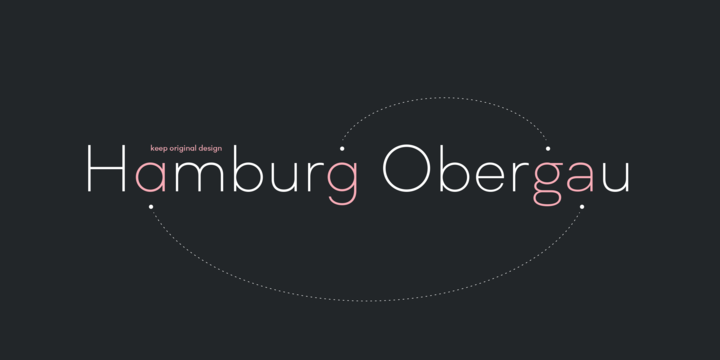
Ich glaube, die Xaloc hatten wir hier noch nicht. 24 Fonts für 120 Euro, sehr gut ausgebaut mit Caption-, Text- und Display-Schnitten, Small Caps und Versal-Eszett (auch als Small Caps regular und kursiv):
Bis morgen gibt es bei MyFonts die gut ausgebaute Kareemah sehr günstig (»ligatures, alternates, small caps,old style figures, fractions, superiors, inferiors and more« – das »more« beinhaltet unter anderem auch ein Versal-Eszett):
Leider ist ẞ anscheinend nicht als U+1E9E kodiert, sondern nur als Kapitälchen enthalten. Und die ungarischen Vokale passen mal wieder nicht. :cry:
Zu FUSE V.2:  Habe die Pakete mal gekauft u. festgestellt, daß beim TEXT Package unter WORD keine Tabularziffern einstellbar sind. Nach den Glyphen müßten die drin sein - sehr ärgerlich.
Oder irre ich mich?
Dieser Mangel ist mittlerweile behoben; es gibt jetzt sowohl Tabular- als auch proportionale Ziffern in allen Schnitten. Mediäval- und Versalziffern sind auch weiterhin zwischen Display- und Textschnitten aufgeteilt – was ja in dem Sinne kein Fehler ist.
Ich sehe gerade, dass es nun die Neue Haas Unica im Sonderangebot gibt (gut ausgebaut in neun Strichstärken, jeweils mit passender Kursive und mit Kapitälchen, hoch- und tiefgestellten Ziffern, hochgestellten Buchstaben und Small-Caps-Eszett):
Eine andere Schrift im Sonderangebot, die mir ganz gut gefällt und die auch sehr gut ausgebaut ist (mit Latin Small Letter Sharp s):
Auf den ersten Blick:
• ß zu breit?, zu B-mäßig, zu »komisch« als Standardvariante
• kein ẞ
• Anführungszeichen zu fett?
• wieder mal nicht zu gebrauchen fürs Ungarische
• das 2-stöckige a wirkt durch die sehr lange und sehr gerade »Gürtelline« sehr breit und irgendwie allgemein gewöhnungsbedürftig
• Es scheint gar keine Ligaturen zu geben, nicht mal die gängigen f-Ligaturen. In den leichten Schnitten ist das okay, aber bei den schweren könnte ich mir vorstellen, dass ich sie hier und da vermissen würde.
Wie gesagt: Ich finde das ›g‹ ganz nett, und man muss schon lange suchen diese komplexe g-Version in einer geometrischen Sans zu finden. Spontan fallen mir da nur die Neutraface, Apercu oder Averta als überzeugendere Kandidaten ein.
Aber Eure Kritikpunkte haben mein Bauchgefühl bestätigt, lieber die Finger davon zu lassen. :nicken::gimmifive: